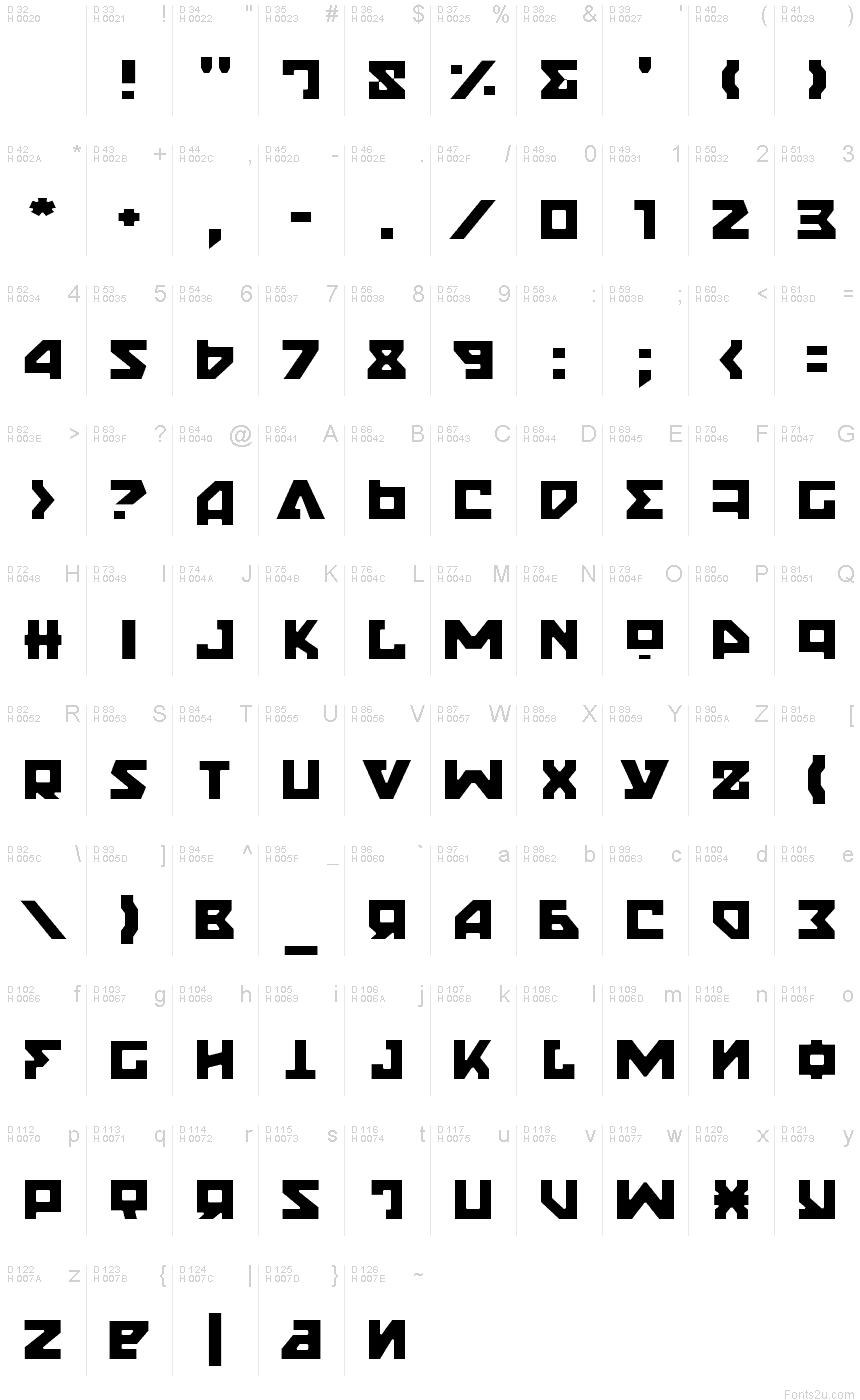
Nyet Light od Iconian Fonts to darmowy techniczny krój pisma w stylu rosyjskim, charakteryzujący się ostrymi, blokowymi formami i przyciętymi otworami, które nadają każdemu słowu wyrazistą sylwetkę. Proste krawędzie i gwałtowne zmiany kątów sprawiają, że napisy są spójne i nabierają unikalnego, graficznego charakteru.
Dzięki temu Nyet Light to solidny wybór na plakaty, okładki albumów, tytuły gier, etykiety, logotypy tematyczne oraz ulotki, które potrzebują akcentu inspirowanego estetyką rosyjską. Sprawdza się szczególnie w krótkich tekstach eksponowanych, gdzie kanciaste kształty tworzą efektowny przekaz bez potrzeby dodatkowych dekoracji.
Nyet Light